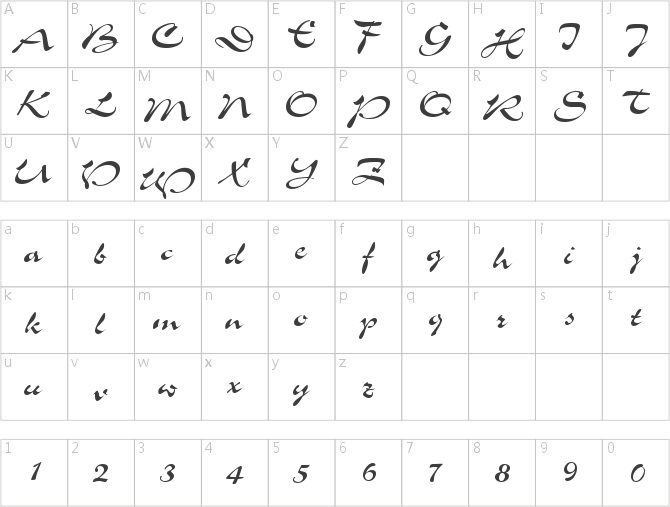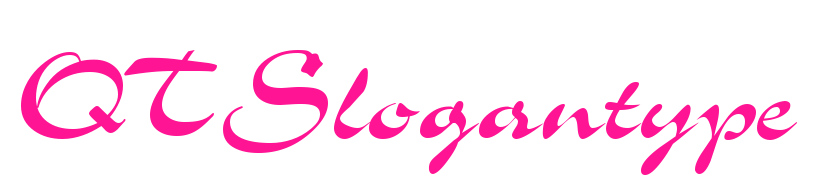
QTSlogantype 詳情頁
字體名稱: QTSloga
QTSlogantype介紹
QTSlogantype字體字庫是一款讓人賞心悅目、百看不厭的英文字體,適合各類廣告和產(chǎn)品包裝設(shè)計應(yīng)用,字體大小0.04MB,格式為ttf字體,上傳用戶是曉語無聲,作者/版權(quán)方為未知